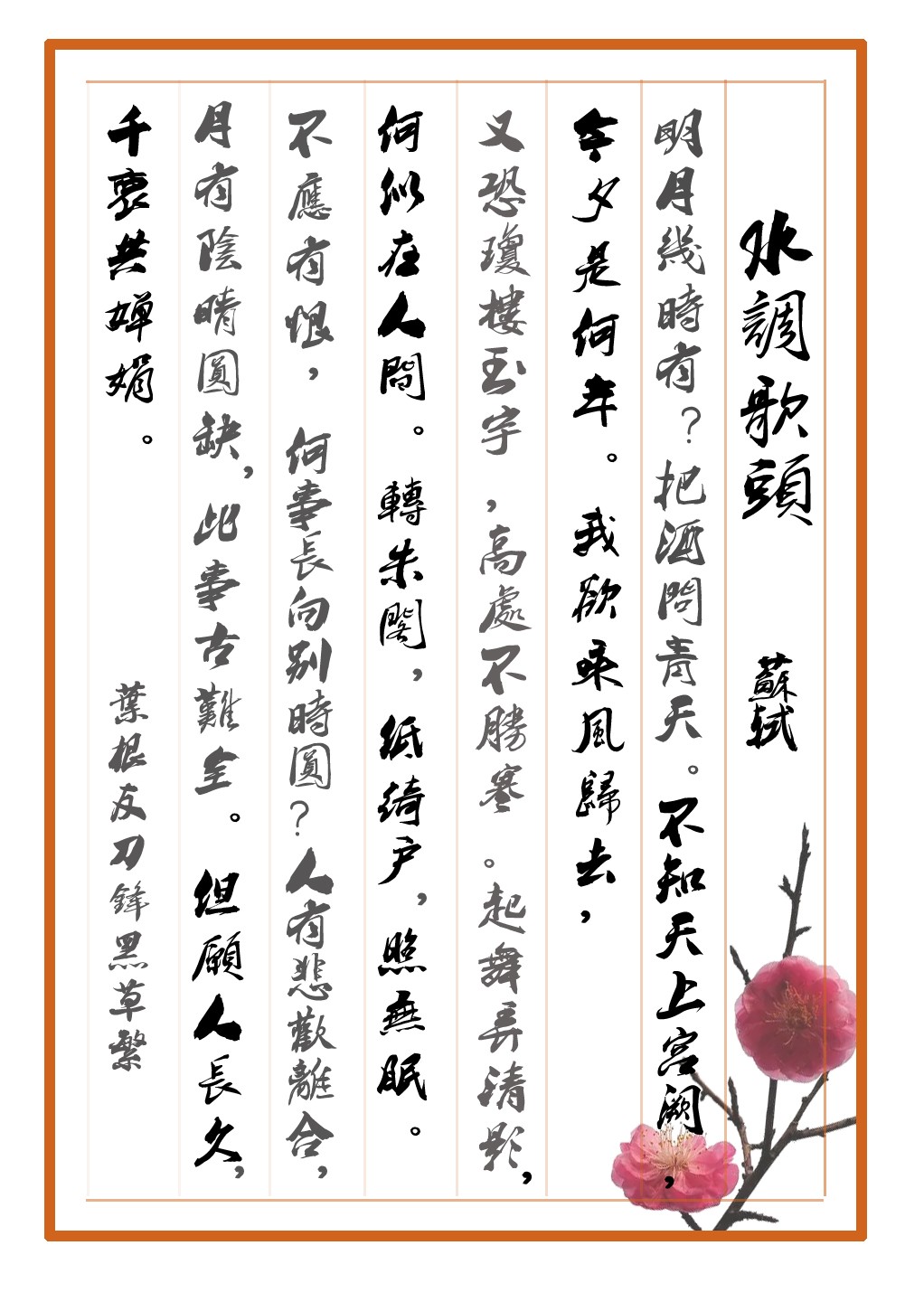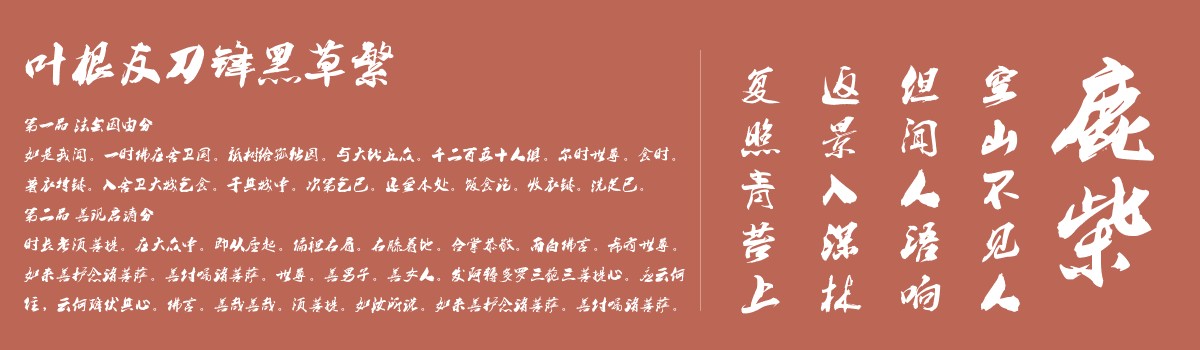
叶根友刀锋黑草繁
这是一款叶根友字体系列最受欢迎的字体之一。叶根友刀锋黑草繁体版本是应广大网友的一致意见,经过三年时间的不断修正优化开发而成,该字体笔画风格犹如刀锋剑影,笔起笔落间一股侠客风的力量萦绕在字里行间,赋予了中国汉字的一种新的犀利,行书与叶氏创新书法的结合,无不演绎出不同的汉字角度。叶根友刀锋黑草广泛应用于社会各界的广告招牌、影视作品以及游戏应用等。叶根友刀锋黑草繁也是一款刀锋犀利的笔画结构,在字体风格上,追求了一种鲜明向上的特点,使整个字型灵动而不失严谨,飘逸俊秀,保留了书法原作的原始元素。